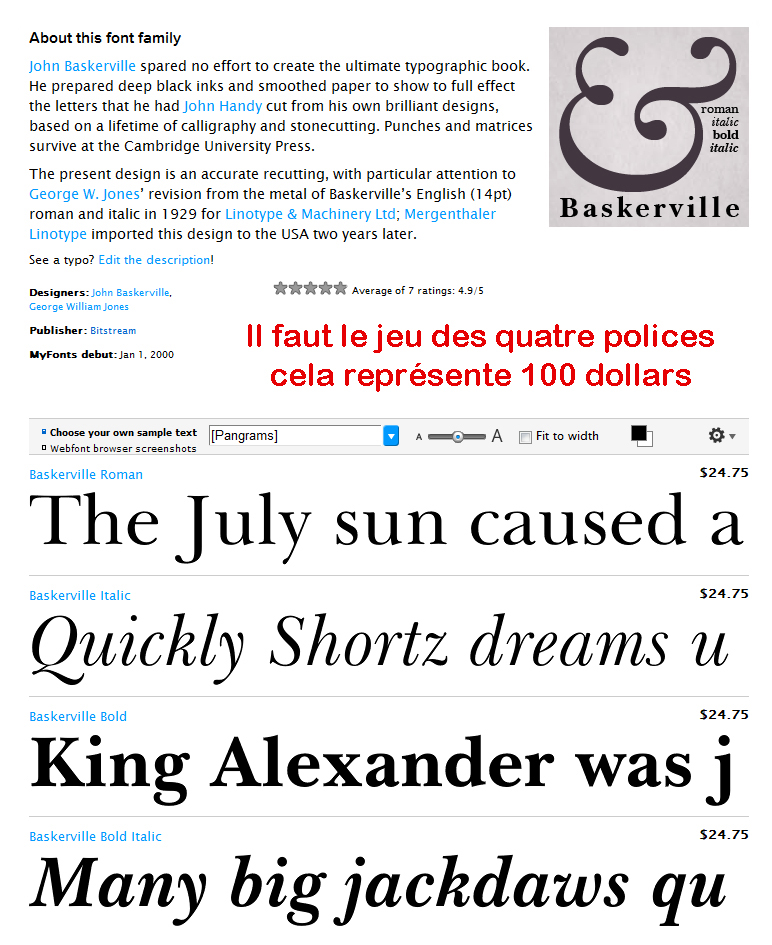
Suite à mon apprentissage de la typographie et à mon exploration de Windows, je soumets à votre sagacité les sujets d'étonnement ci-dessous.
J?ai l?intention d?acheter le Baskerville pour mon ordinateur à cause du J qui me plaît vu que je m?appelle Jean.
J?ai vu que sur My Fonts qu?il y a 4 polices : regular, iltalic, bold et bold italic pour un prix de 25 $ pièce, soit un total de 100 $. 1) Pour savoir si je devais acheter les 4, je suis allé voir dans Wimdows / Fonts et j?ai vu que pour le Garamond, il n?y a que 3 polices, regular, italic et bold qui me permettent cependant les 4 possibilités dans Word 7 : regular, iltalic, bold et bold italic ; ceci est mon premier sujet d?étonnement. 2) Voulant en avoir le c?ur net, j?ai enlevé Garamond regular de Windows ainsi qu?italic : sur Word je ne pouvais plus obtenir une écriture normale mais seulement l?écriture en gras mais aussi le gras en italique alors qu?italic n?était plus dans Windows ; ceci est mon deuxième sujet d?étonnement. 3) Ensuite je me suis aperçu que le nom des polices que j?avais copiées sur une clé USB, avaient changé de nom, voir images ci-jointes ; ceci est mon troisième sujet d?étonnement. 4) Hier, j'ai téléchargé Berthold Baskerville et après essai avec cette seule police gratuite j'obtiens les 4 cominaisons dans Word ; ceci est mon quatrième sujet d'étonnement.
5) En conclusion, dois-je vraiment acheter les 4 polices du Baskerville pour obtenir les 4 combinaisons dans Word : regular, iltalic, bold et bold italic ? 6) PS : le J du Baskerville de My Fonts ne m?emballe pas, en existe de plus élégant ?